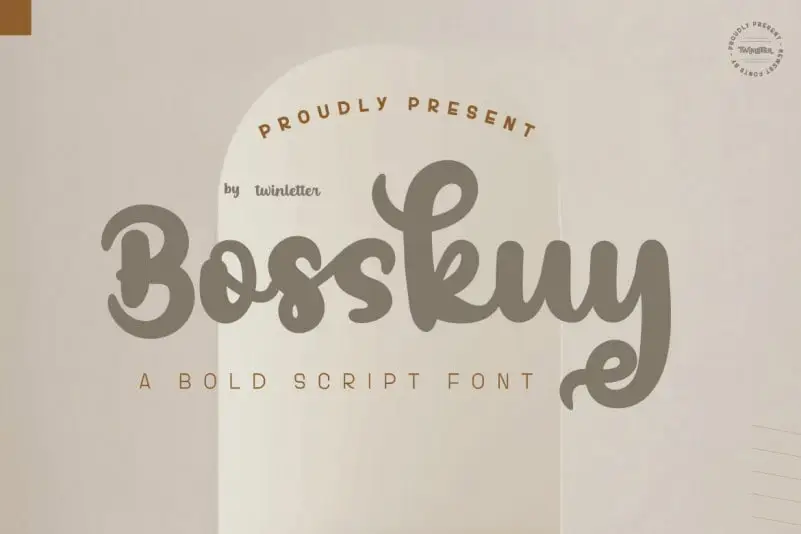
Aqui está uma descrição em português do Brasil para a página de download da font ‘Bosskuy Script Font’: Essa é uma fonte script curva e grossa, criada para dar um toque elegante a seus projetos com headlines e logotipos. A Bosskuy Script é perfeita para adicionar um ar nostálgico às suas criações gráficas. Suas linhas são fortes, confiantes e dinâmicas, ideal para complementar os elementos de destaque em sua marca ou projeto. Essa fonte não apenas adicionará charme à sua identidade visual, mas também ajudará a realçá-la com um toque de nostalgia que certamente marcará sua marca.